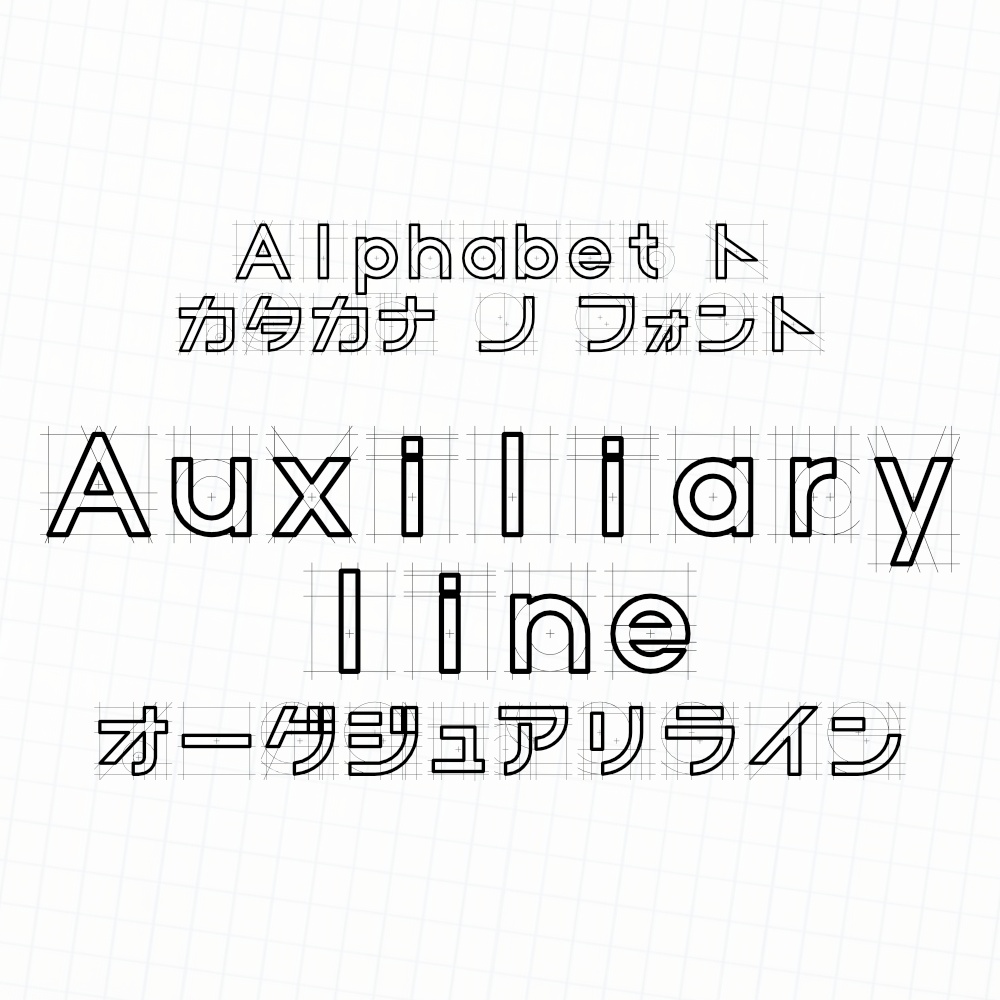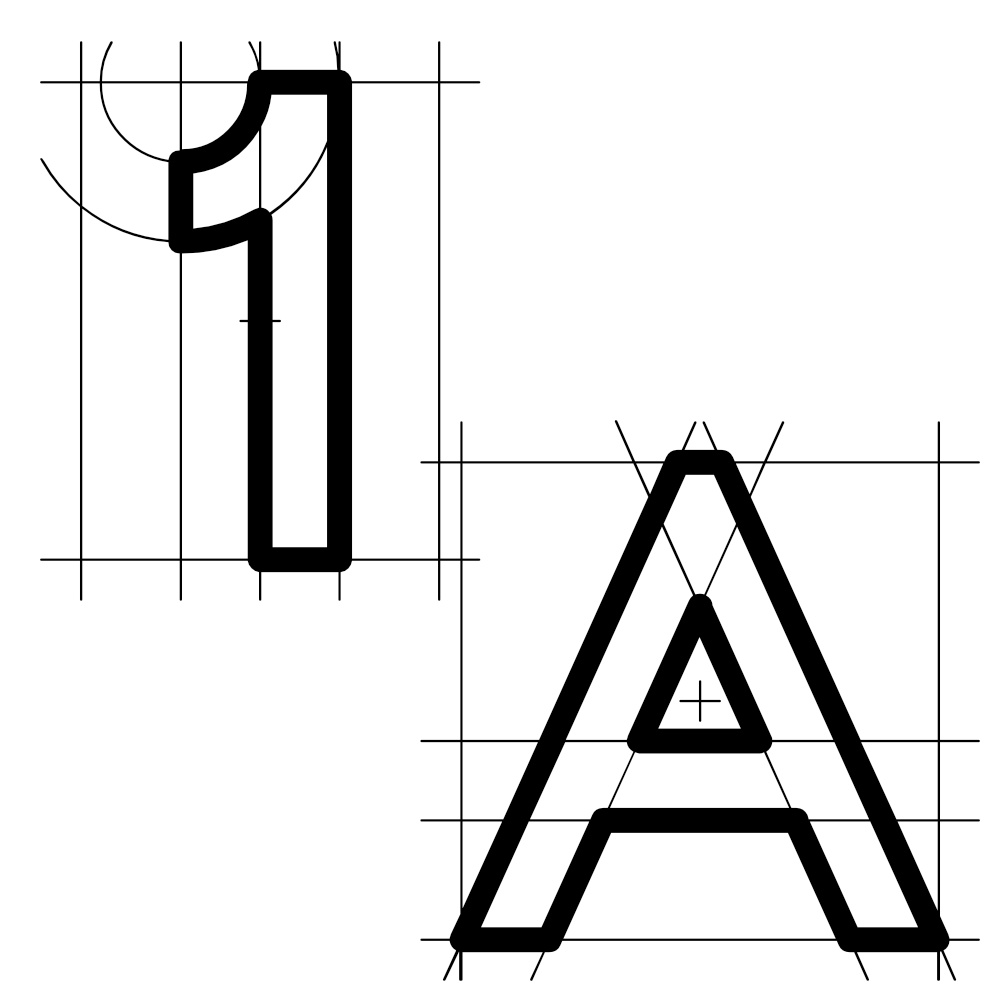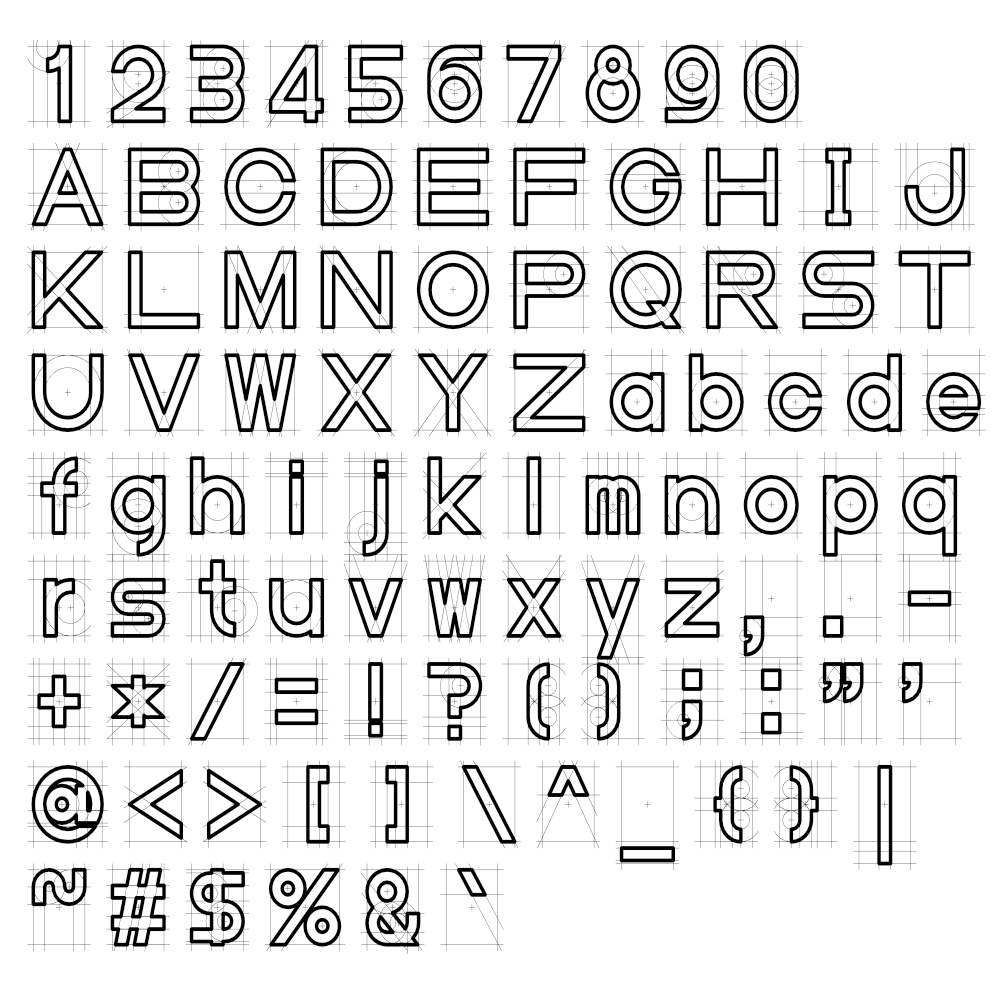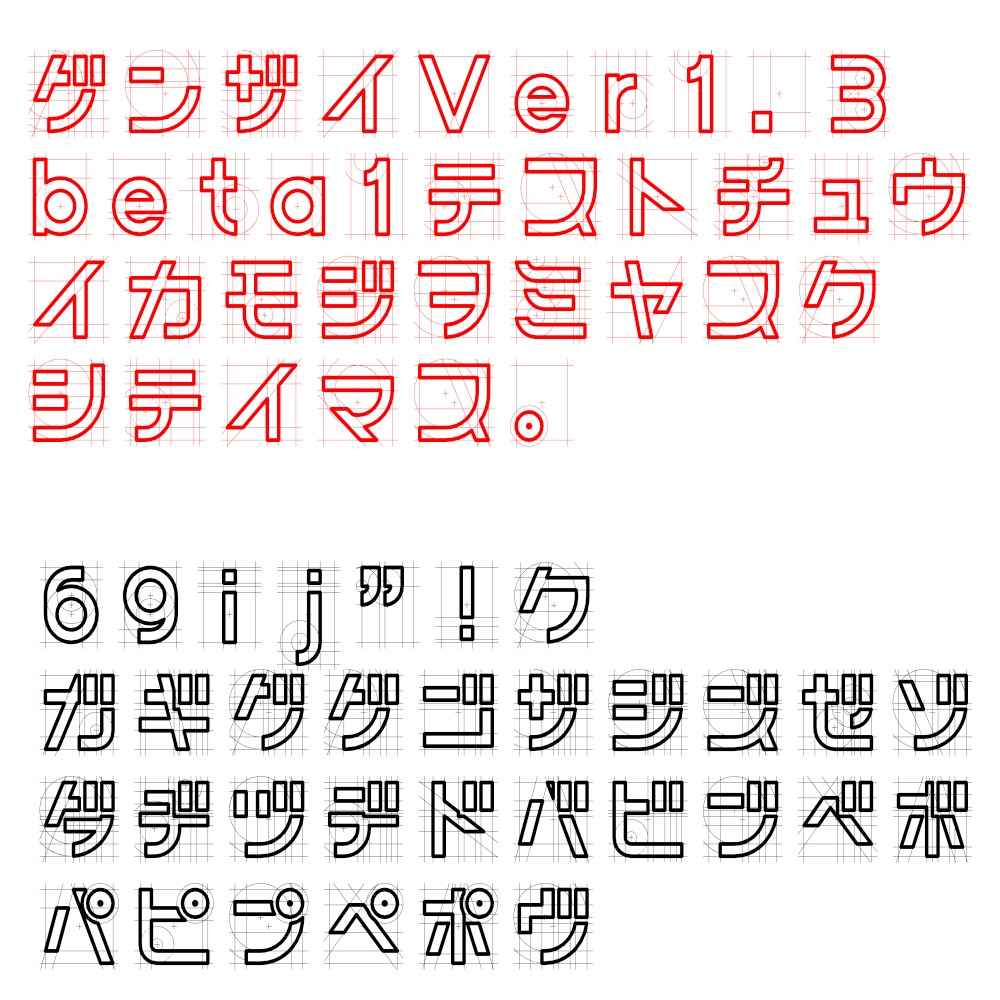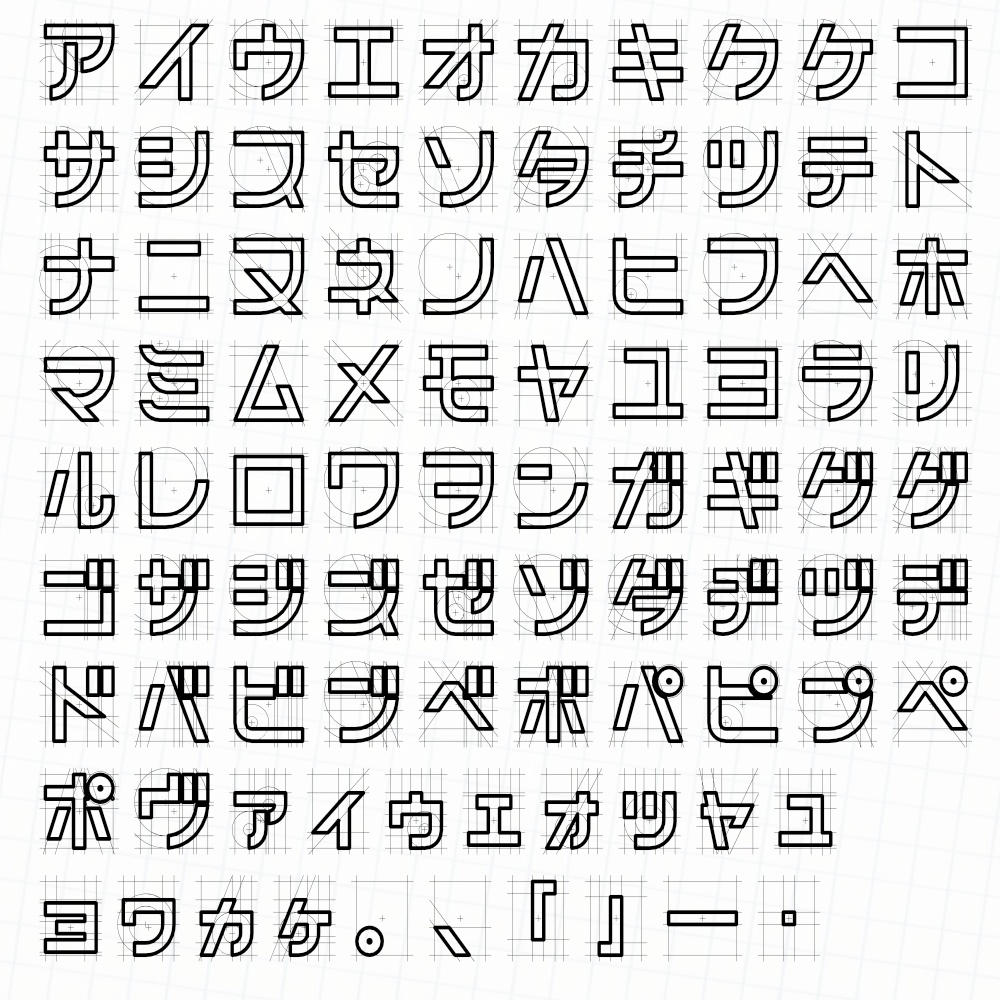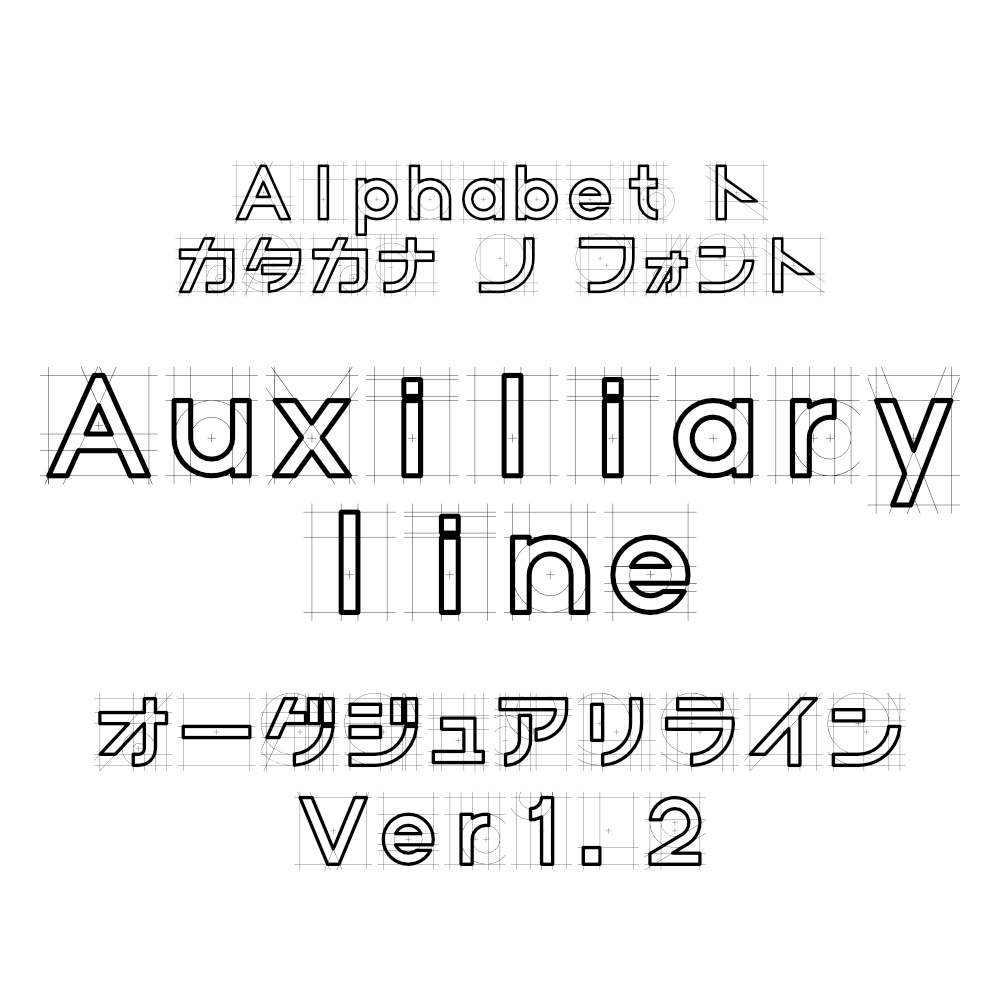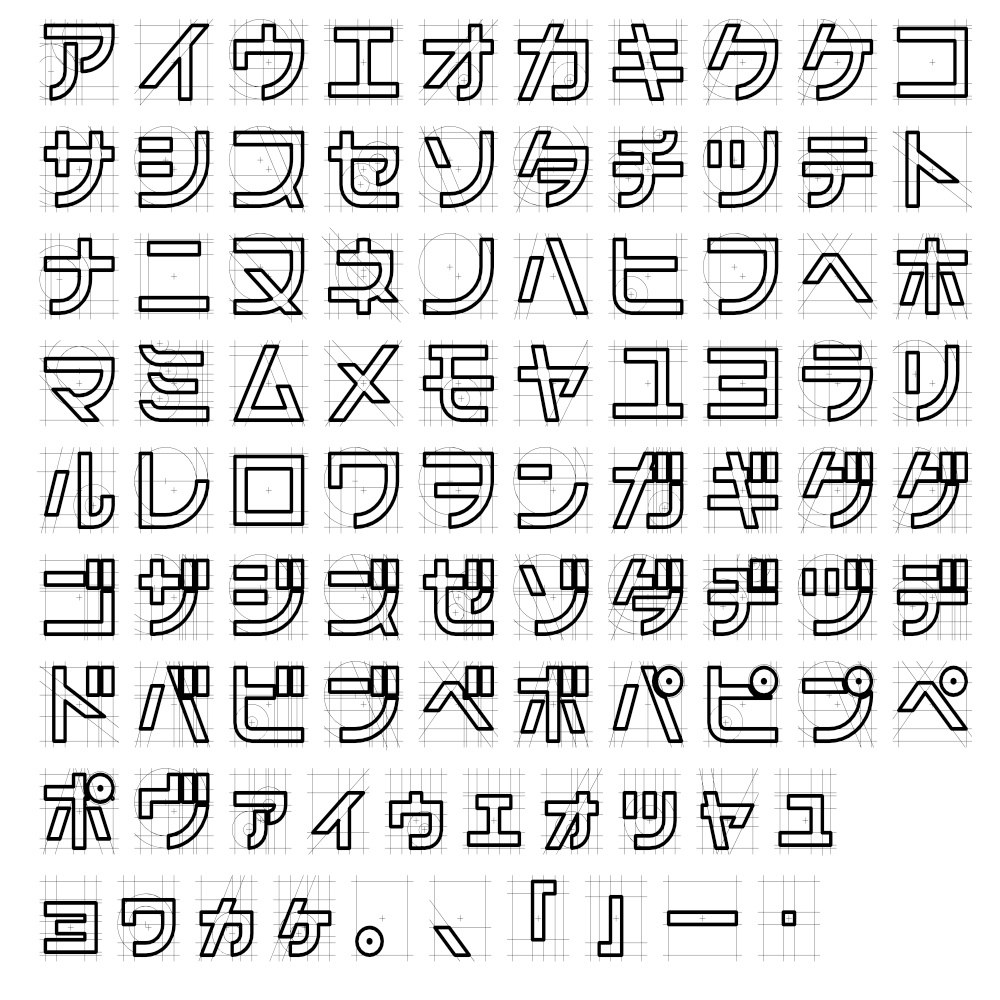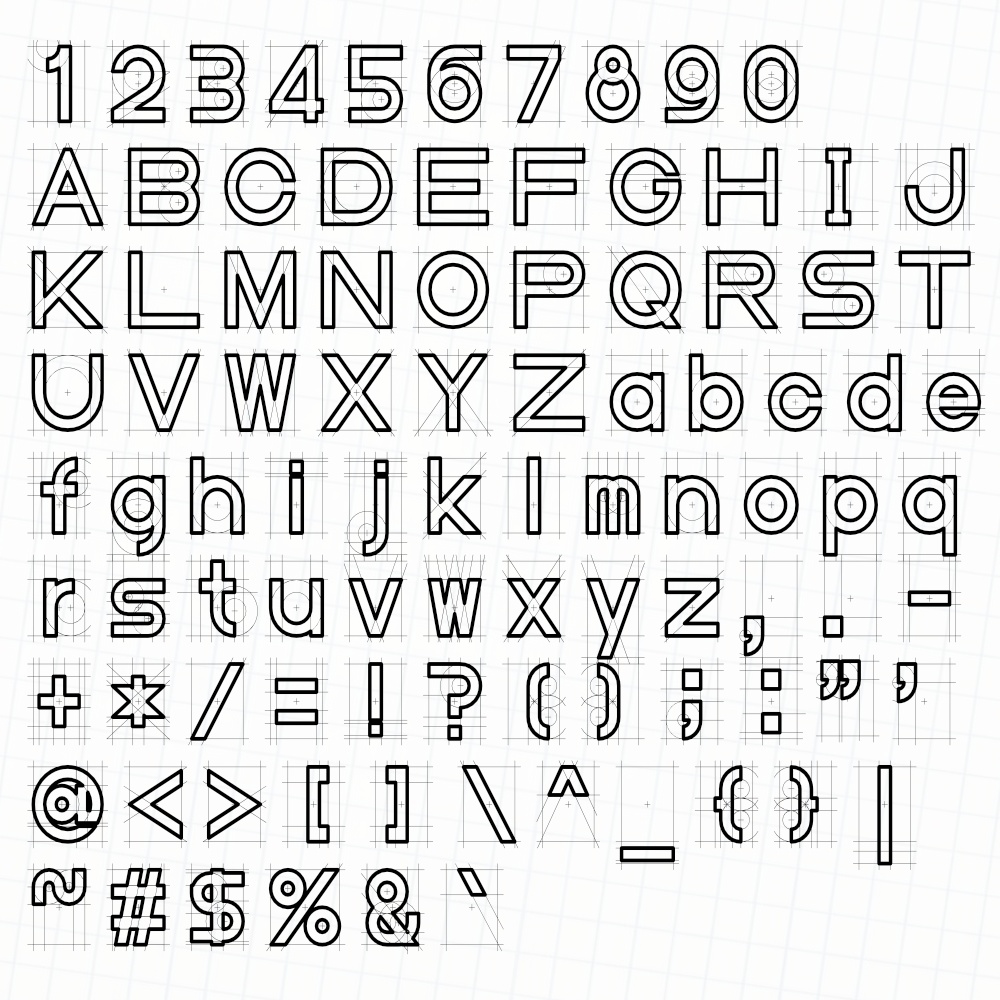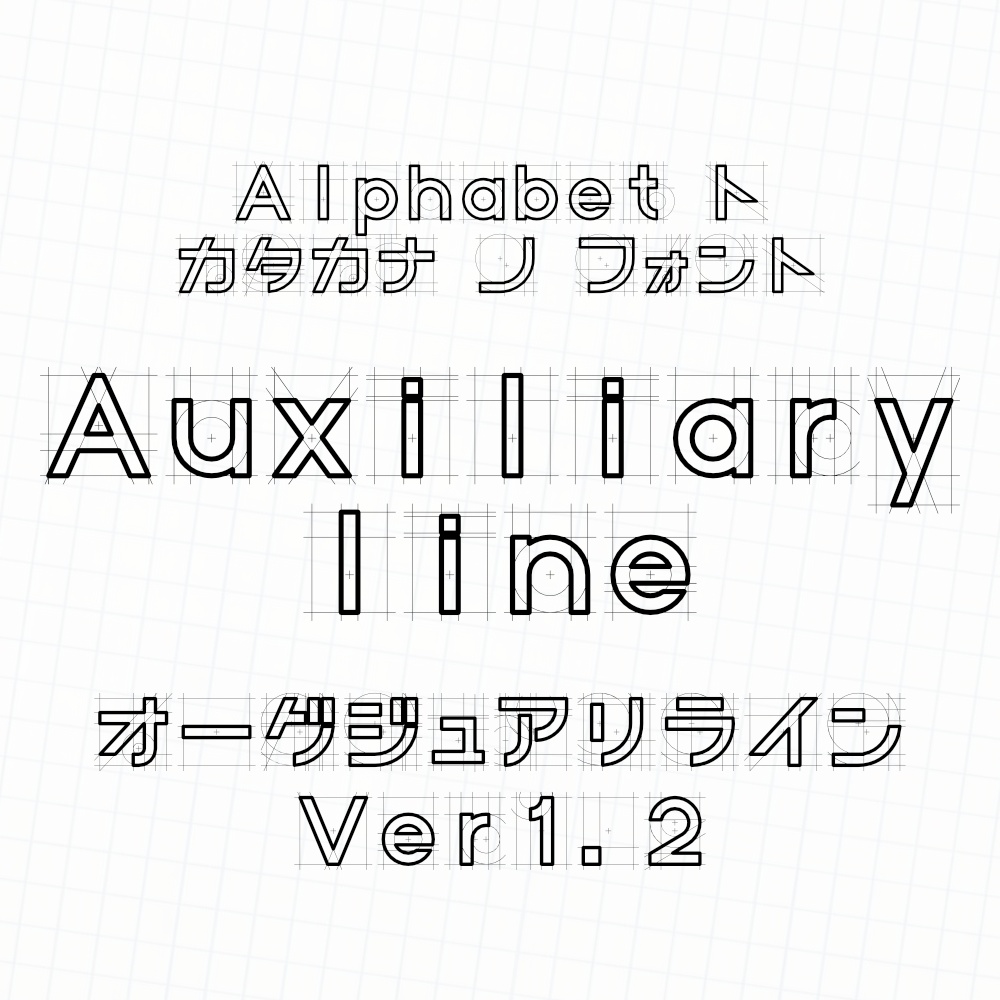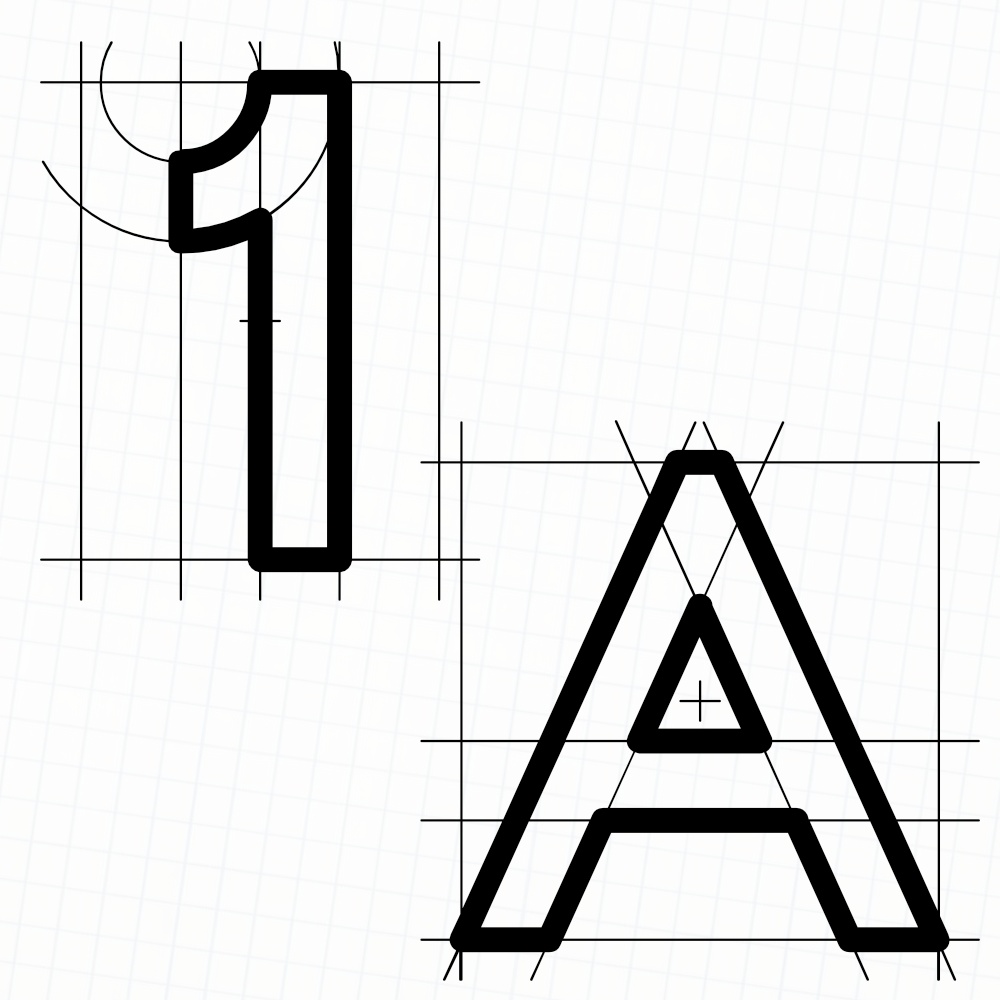
フォント Auxiliary line オーグジュアリライン
補助線を残しました。 ダウンロードファイルの違いは以下になります。 v1.3 : ひらがなの追加と文字を見やすくする対応 v1.2 : 濁点半濁点カナについて、線を重ねない v1.1 : 濁点半濁点カナについて、線を重ねる (公開終了しました)
2026/10/06 v1.3 ひらがな追加版の公開 - 軽微な修正[れぁ] 2026/10/03 v1.3β4 ひらがなの修正 - バランス調整[いおこごぃのゆしじるろにつづ] 2026/09/29 v1.3β3 グリフの追加 - ひらがなを追加 2026/09/27 v1.3β2 グリフの見直し - 小さく見えていた文字を大きくした[テマ] - 大きく見えていた文字を小さくした[ス] ※保留[ヌフワヲ] - 位置を下にずらした[コゴニユヨロ] 2026/09/27 v1.3β1 グリフの見直し - 気に入らない字形の修正[69] - ストロークが隣接するとその部分が濃く見えるため、少し離し軽減させた[ij!"≪濁点半濁点カナ≫] - 字形が似ていて判別が付きにくくなっていたのを少し修正[クグ] - 濁点/半濁点カナのパス作成方法を見直し、修正が行いやすくした。 2026/09/27 v1.3β1 グリフの見直し - 気に入らない字形の修正[69] - ストロークが隣接するとその部分が濃く見えるため、少し離し軽減させた[ij!"≪濁点半濁点カナ≫] - 字形が似ていて判別が付きにくくなっていたのを少し修正[クグ] - 濁点/半濁点カナのパス作成方法を見直し、修正が行いやすくした。 2026/08/06 v1.2d 修正 - affinity でフォントスタイルが"_v1.2"になる現象を修正 2026/08/04 v1.2c 文字の修正 - 文字が欠けていたのを修正(メモに残さず修正したので修正対象を記載しません) - 補助線がはみ出ていたのを修正[1r] 2026/08/03 v1.2b 文字の修正 - ズレの修正["] 2026/08/03 v1.2a 文字の修正 - 濁点カナについて、見えない線ゴミが残る問題を修正 - 試しに漢字3つ追加[補助線] 2026/08/01 v1.2 濁点半濁点カナについて、線が重ならないように修正 2026/08/06 v1.1c 修正 - affinity でフォントスタイルが"_v1.1"になる現象を修正 2026/08/04 v1.1b 文字の修正 - v1.2bとv1.2cの修正取り込み 2026/08/01 v1.1a 文字の修正 - 線が太かったのを修正[セゼ] - 誤りの修正[スザズゾプ] 2026/07/15 v1.1 カタカナの追加 2026/07/15 v1.0b 文字の修正 - 実線が余計に存在していたのを修正[{}()] 2026/07/15 v1.0a 文字の修正 - 補助線が失われていたのを修正[L] - 実線が余計に存在していたのを修正[P] - 補助線がはみだしていたのを修正[f] 2026/07/14 v1.0 初版